Đã bao giờ bạn tự hỏi rằng liệu những thương hiệu nổi tiếng sử dụng Font chữ gì để sáng tạo ra Logo của họ hay chưa? Có thể thấy rằng, hiện nay trên thị trường có rất nhiều những thương hiệu nổi tiếng, đi kèm theo đó là những Logo mang đậm chất riêng mà họ sáng tạo ra để giúp nhận diện thương hiệu.
Logo được hiểu là sản phẩm trực quan, có thể bao gồm hình ảnh, chữ viết hoặc cả hai giúp người tiêu dùng nhận diện được thương hiệu cá nhân của nhãn hiệu. Ngoài tính chất đại diện, Logo còn giúp truyền tải những thông điệp từ người sáng tạo đến với mọi người. Vì vậy mà khi thiết kế Logo, những người sáng tạo cần phải chú ý rất nhiều đến việc lựa chọn Font. Font chữ cần phải đáp ứng được những tiêu chí của của Logo để có thể toát lên được ý nghĩa mà bạn muốn truyền tải. Chính vì thế mà trong bài viết này, Gitiho sẽ giới thiệu đến bạn một số Font chữ mà các thương hiệu nổi tiếng sử dụng để thiết kế Logo bạn nhé.
Một Logo được thiết kế sẽ phải đáp ứng những yêu cầu từ phía doanh nghiệp, tổ chức. Tùy vào từng yêu cầu mà các Logo sẽ mang những nét riêng trong đó, có Logo sẽ mang vẻ tối giản sang trọng, nhưng có Logo toát lên vẻ mạnh mẽ, … Và để thể hiện đúng tính chất của Logo thì việc lựa chọn Font chữ là vô cùng quan trọng. Chính Font chữ mà bạn chọn sẽ thể hiện lên những yêu cầu của khách hàng, giúp thương hiệu thành công và khiến cho Logo trở nên ấn tượng và phổ biến hơn với khách hàng. Từ đó, mức độ uy tín và sự chuyên nghiệp của công ty sẽ được mọi người nhìn nhận.
Thiết kế Logo sẽ tạo cho thương hiệu một bản sắc riêng, bản sắc sẽ tạo ấn tượng trong mắt người tiêu dùng, tăng tỉ lệ mua hàng dựa theo ấn tượng ban đầu của họ. Dù thương hiệu kinh doanh theo nhiều hình thức truyền thống hay trực tuyến, ngay cả doanh nghiệp có sản phẩm tốt nhưng có một bộ nhận diện kém trong đó có Logo thì mức độ cạnh tranh của thương hiệu thấp, khó thuyết phục khách hàng vì khách hàng đánh giá dựa trên ấn tượng hình ảnh, sự chuyên nghiệp của thương hiệu. Vì vậy để tạo ra được nét đặc sắc riêng cho Logo, việc lựa chọn Font chữ là vô cùng quan trọng. Mỗi một phông chữ sẽ mang một nét riêng và từ đó Logo cũng sẽ mang những nét đặc sắc đó.
Việc mỗi một Logo có một Font chữ riêng để thiết kế sẽ giúp cho Logo đó có nét riêng và giúp người dùng dễ dàng nhận diện, phân biệt nhãn hiệu này với nhãn hiệu khác. Khi có một thiết kế Logo ấn tượng, chuyên nghiệp sẽ tạo nên sự đồng bộ giúp khách hàng có thể dễ dàng ghi nhớ và nhận biết thương hiệu.
Với nhóm Logo này, bạn sẽ thấy có một hình nổi bật ở chính giữa và đi kèm với tên của nhãn hiệu. Thông thường nhóm Logo này sẽ được thiết kế mang hướng tối giản nên các Font chữ được chọn để thiết kế sẽ thường cứng cáp, không quá màu mè nhưng vẫn gây ấn tượng với người xem.
1. Avant Garde Gothic Demi (Adidas)
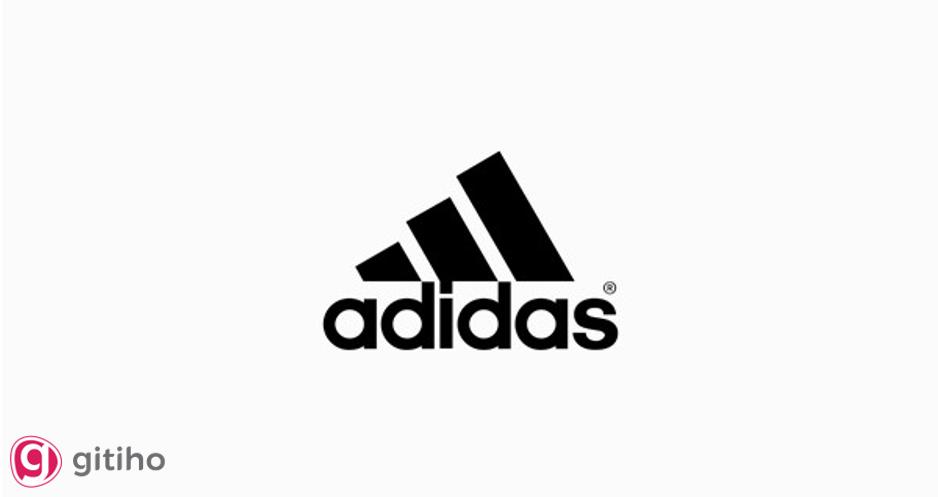
2. Myriad Pro Bold Condensed (Adobe)
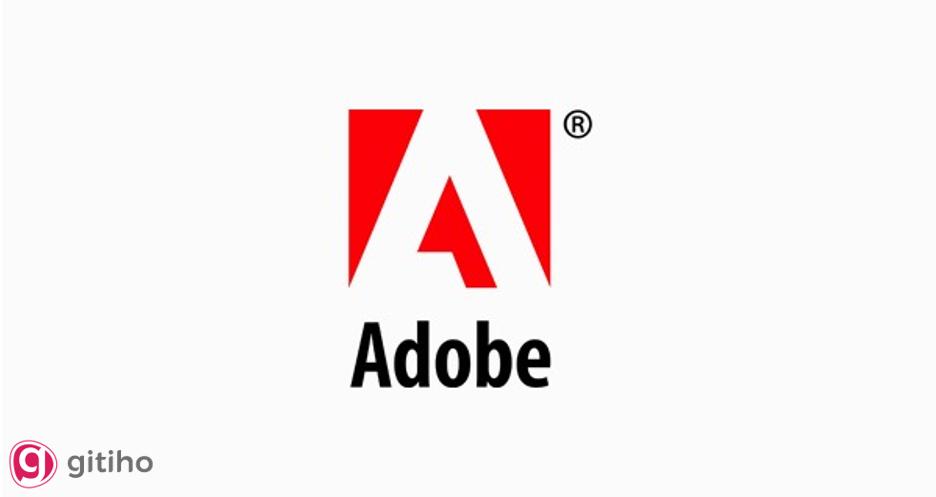
3. Garamond (American Eagle)
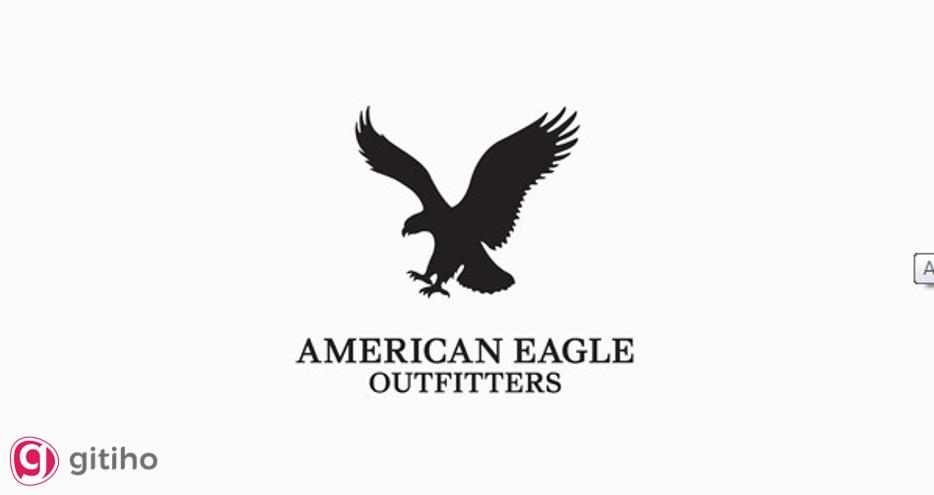
4. Optima Roman (Aston Martin)
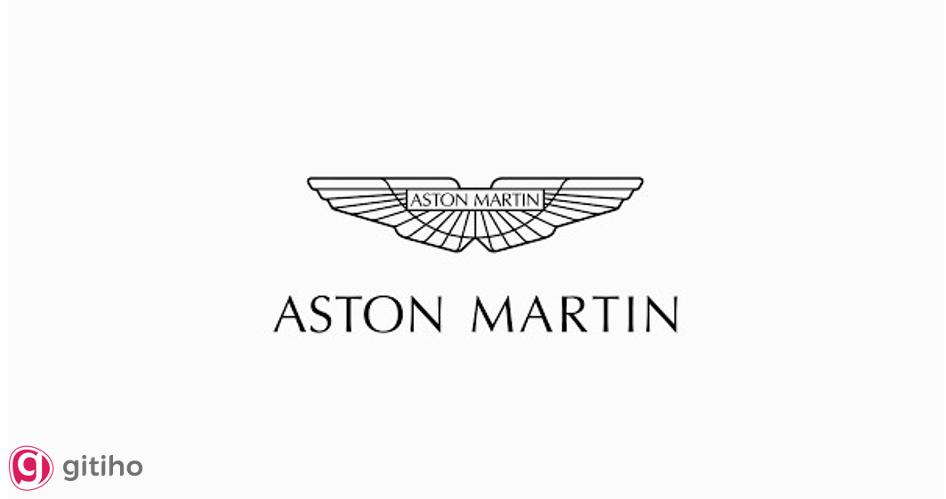
5. Gotham Bold (DC Comics)
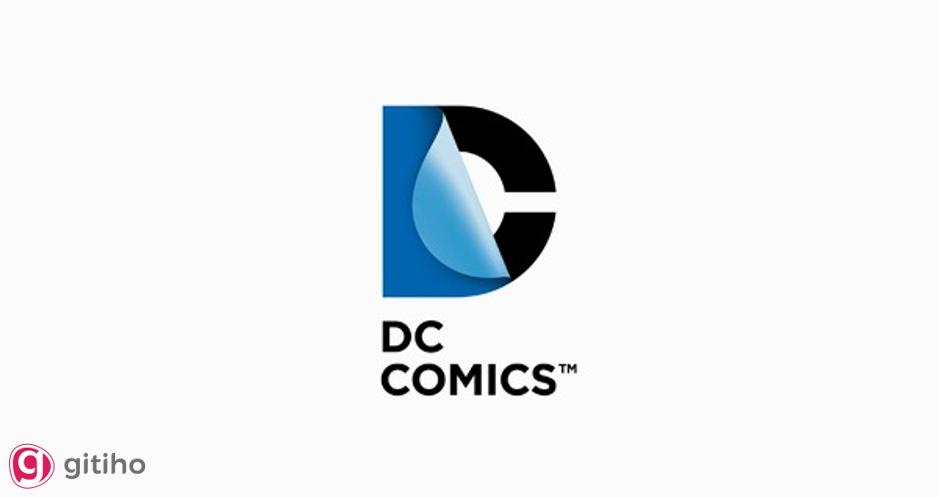
6. Futura Bold Oblique (PayPal)
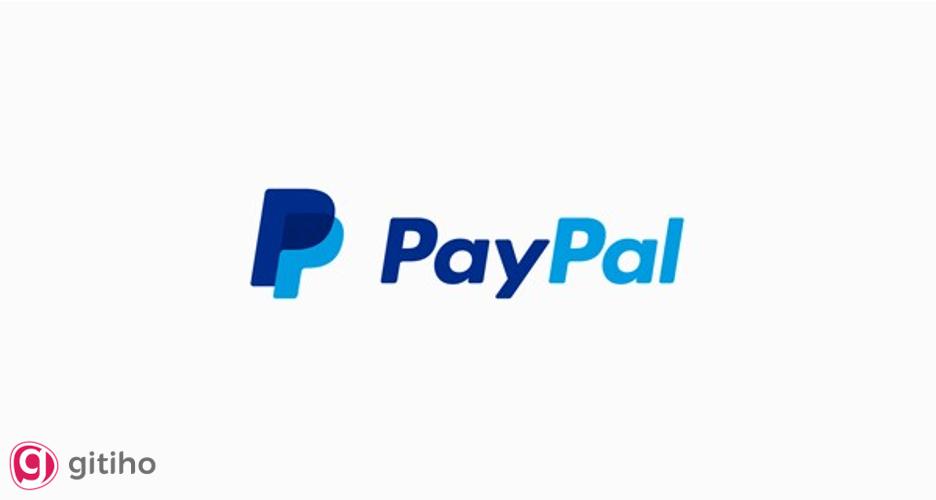
7. My Puma (PUMA)
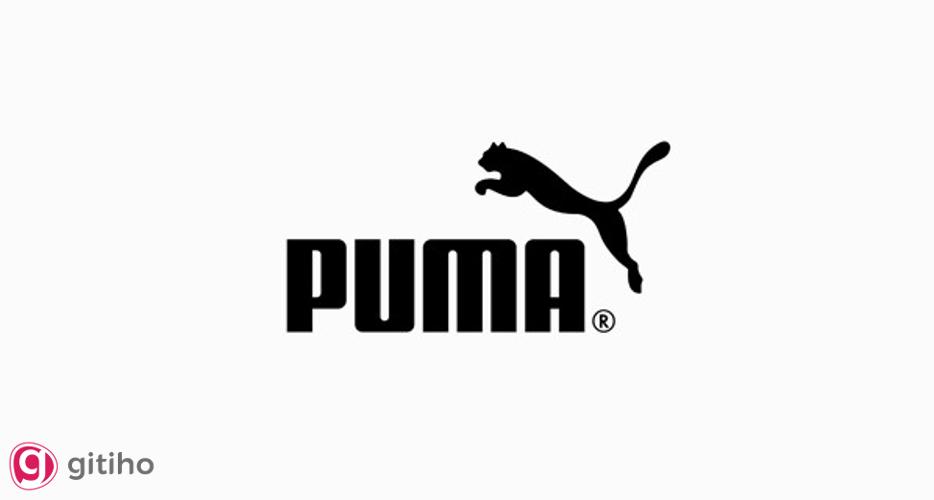
8. LL Circular (Spotify)
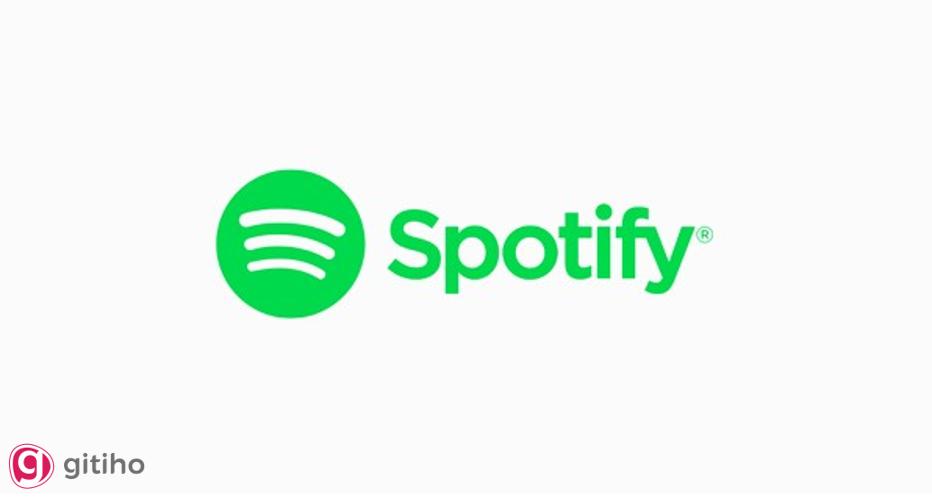
9. Avenir 95 Black (Toyota)
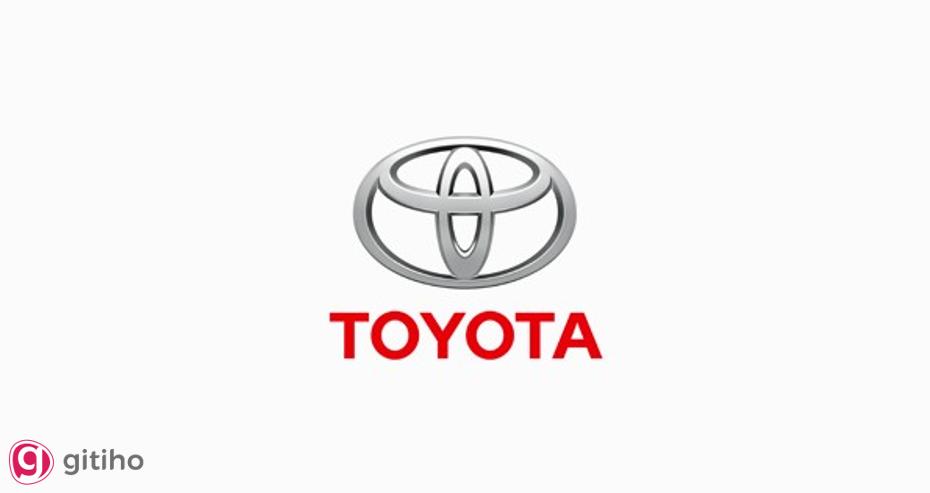
10. Univers Light (UNICEF)
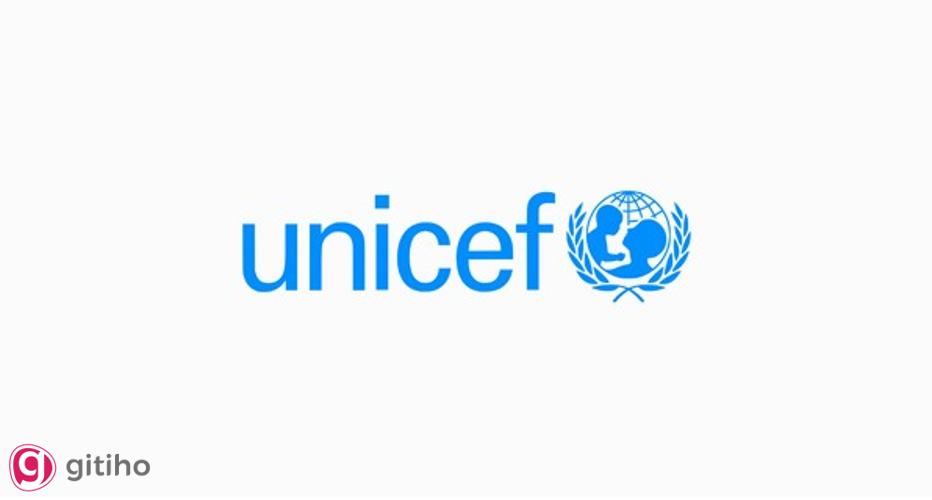
11. Helvetica Neue 75 Bold (WhatsApp)
12. Trade Gothic Bold Condensed No.20 (Youtube)
Với nhóm Logo này, vì phần chủ đạo là phần chữ nên các nhãn hiệu thường lựa chọn những Font chữ mang hơi hướng độc đáo, thậm chí là màu mè để làm nổi bật tên của thương hiệu.
1. Gill Sans Std (BBC)
2. Avant Garde Gothic (Calvin Klein)
3. Eurostile Ext Black (Casio - Toshiba)
4. Futura Demi Bold (Dolce & Gabbana)
5. Univers 53 Extended (ebay)
6. Klavika Bold (Facebook)
7. Futura Bold/ Univers 67 (FedEx)
8. Frutiger Black (Flickr)
9. Futura Extra Black Italic (Gillette)
10. Men In Blue (IBM)
11. Myriad Bold (iTunes - LinkedIn)
12. Helvetica Black (LG - Panasonic)
13. English Towne (The New York Times)
14. PhatBoy Slim (Playstation 3)
15. Myriad Semi Bold (Rolls-Royce)
16. Didot (VOGUE)
17. Myriad Pro Bold (Walmart)
18. Walt Disney Script (Walt Disney)